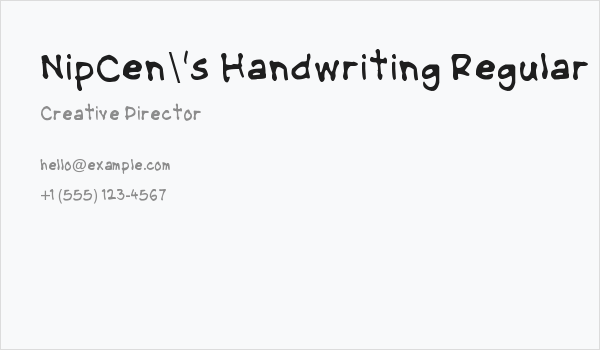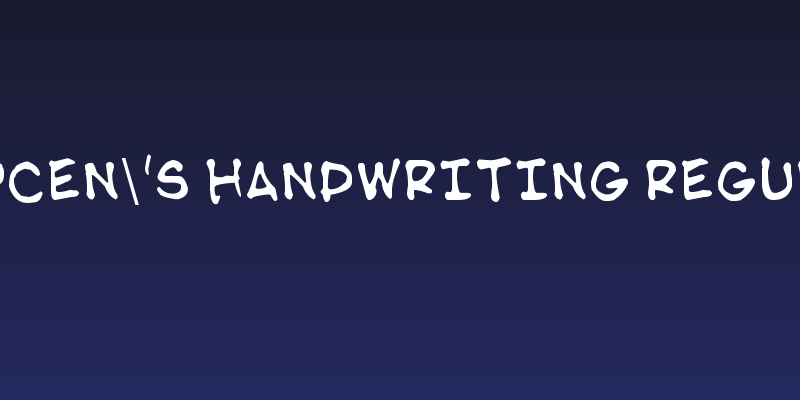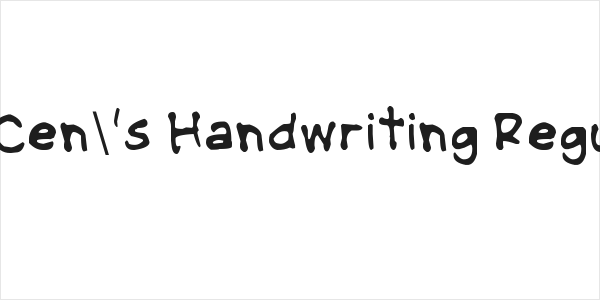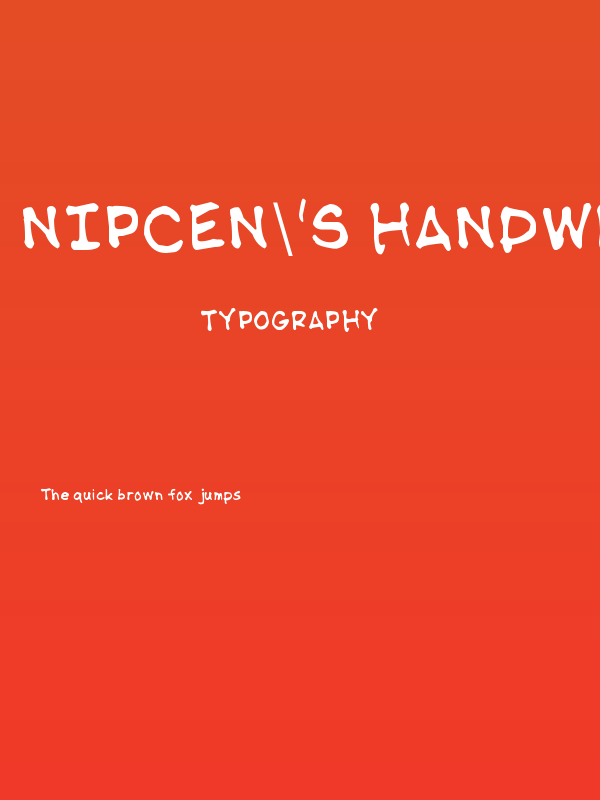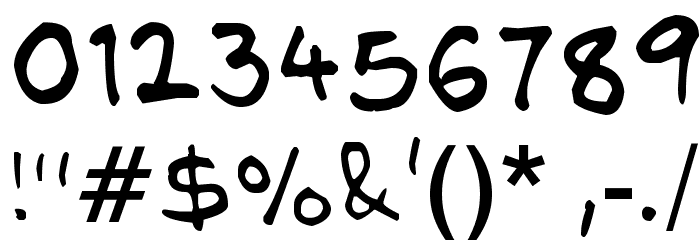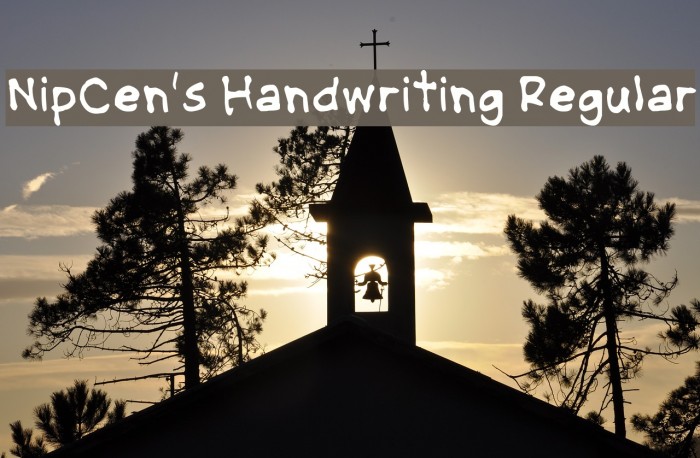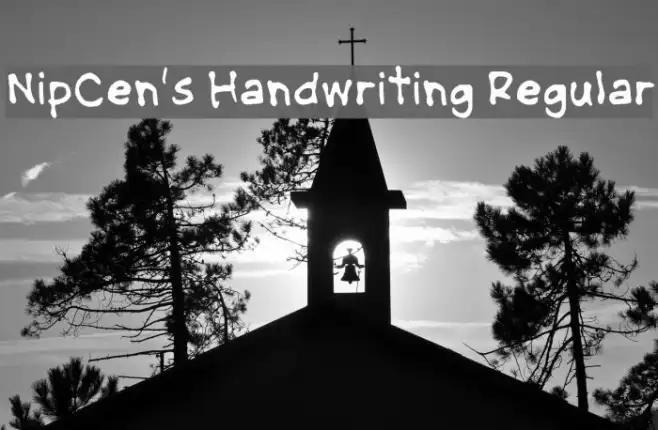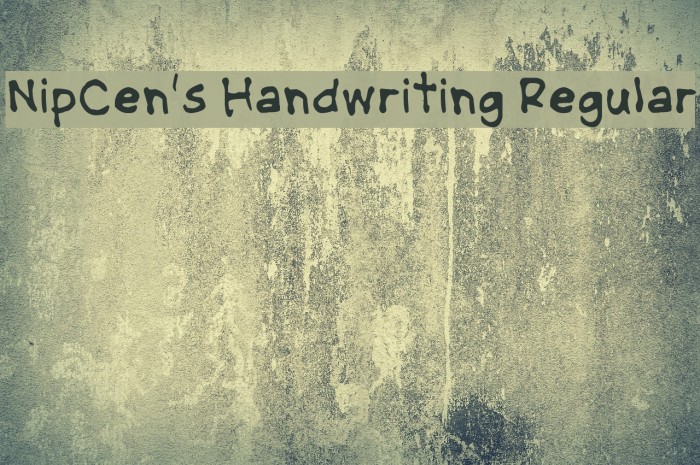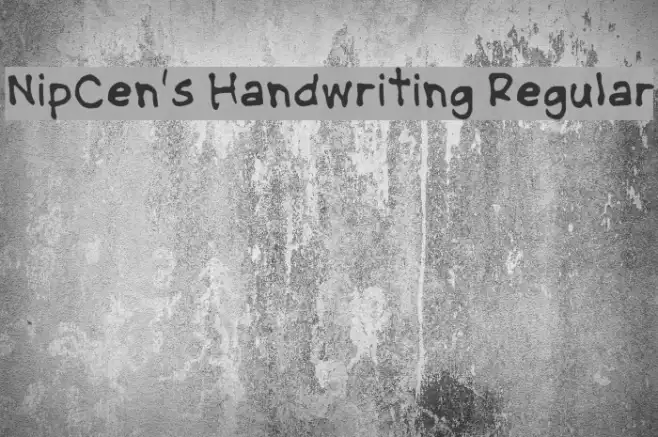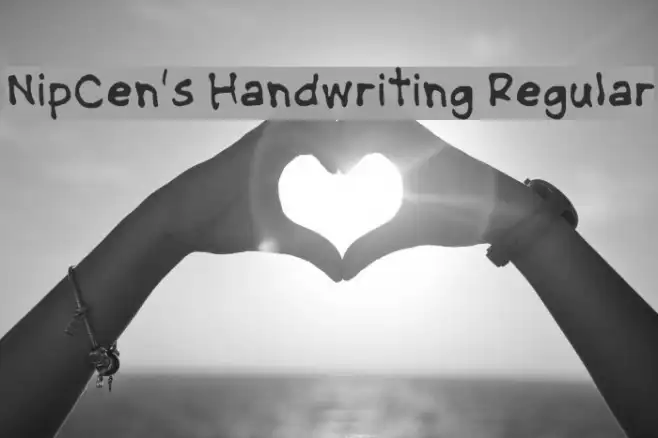
NipCen's Handwriting Regular Font
| Stile generale | Casual, Playful |
| Caso d'uso | Headlines, Logos, Informal Text |
| Progetti proposti | Ideal for children's books, greeting cards, casual branding, and informal invitations. |